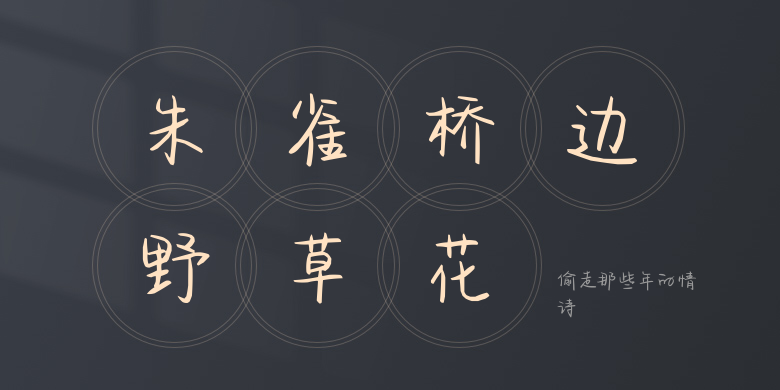
偷走那些年的情诗
偷走那些年的情诗,这款字体结构工整、笔画清晰,兼顾美观与易读性,适用于标题、正文、海报、包装、LOGO 等多种场景。字形优雅稳定,风格百搭耐看,适配日常排版与创意设计,让文字呈现更舒适、更具质感。偷走那些年的情诗一笔一画,皆是细节,以均衡的比例、流畅的线条打造舒适视觉体验,字形端正大气,风格简约现代。无论是商业设计、品牌宣传还是日常排版,都能轻松驾驭,让文字更有格调与力量。偷走那些年的情诗字体下载。